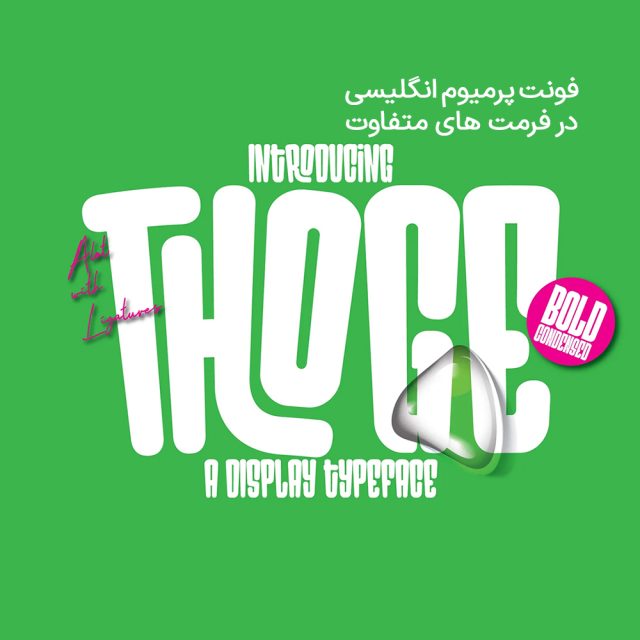
دانلود فونت انگلیسی Thoge Font
فونت پرمیوم و انگلیسی Thoge Font یک فونت شاد و سرزنده است که از بادکنکهای پلاستیکی الهام گرفته شده و با لیگاتورها تکمیل شده و به هر طرحی جلوهای شاد میبخشد و میتواند در پروژههای خلاقانه مختلفی که به دنبال یک سبک تایپوگرافی الهام گرفته از گرافیتی بازیگوشانه و متمایز هستند استفاده شود.